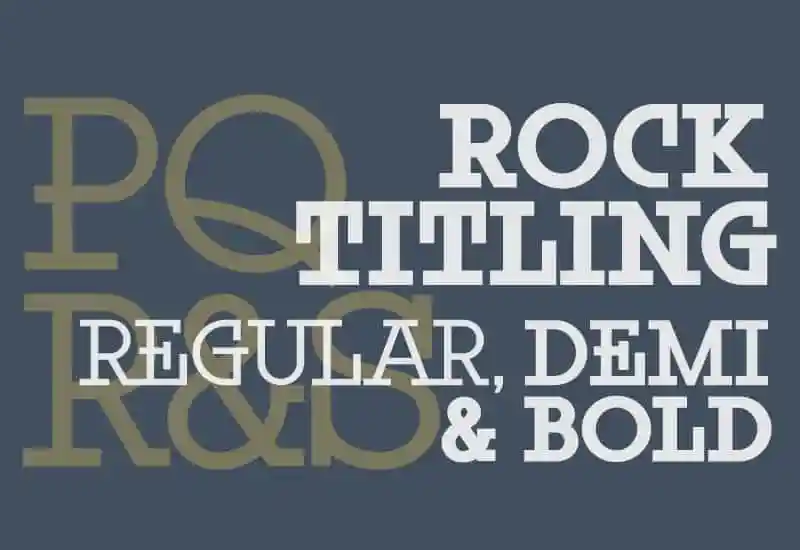
A Rock Titling Slab Serif Font é uma família geometrica de serif slab que traz elementos únicos para destacar seu visual único. Com uma tipografia simples e sofisticada, essa elegante combinação destaca-se com um aspecto limpo e moderno, ainda assim carregando alguns toques levemente retro. Essencialmente uma tipografia egípcia, a Rock Titling Slab Serif é projetada para capturar o espírito contemporâneo enquanto mantém elementos de design vintage. Ela foi criada pela NowType, e traz três pesos: Regular, Demibold e Bold. Esta fonte tem um visual forte e compacto graças aos cestos longos das serifas slab que ela usa de maneira divertida para capitalizar sobre a estética moderna. É perfeitamente adaptável para texturas e layouts que exigem uma aparência robusta e inovadora, sem perder a elegância do design clássico. Para designers e criadores de conteúdo em busca de algo único e atemporal, esta fonte é um excelente escolha, combinando uma visão puramente geometrica com toques retro e uma presença vibrante. Ela se destaca como uma ótima opção para qualquer aplicação onde quer que você precise de um elemento visual distintivo.